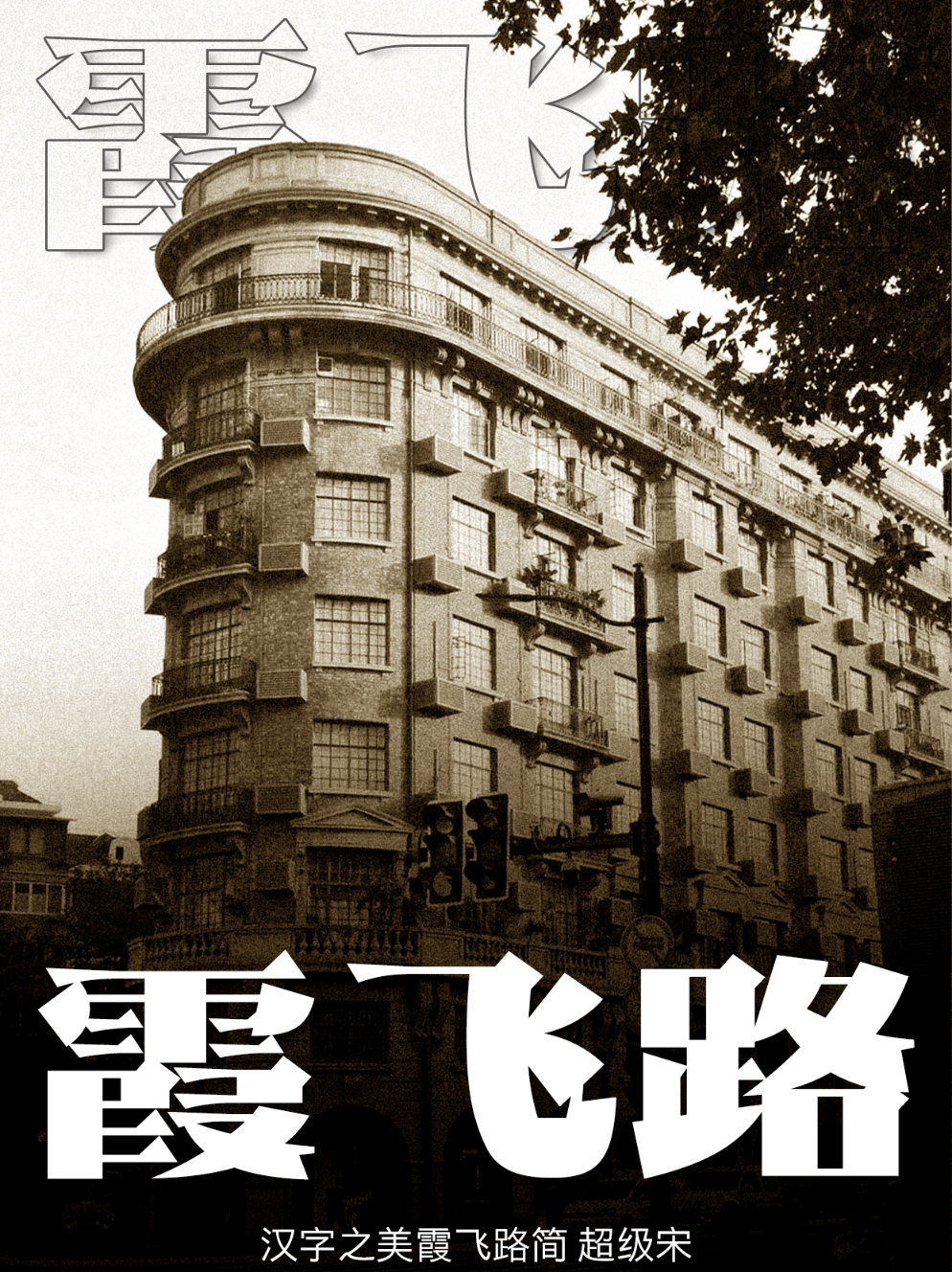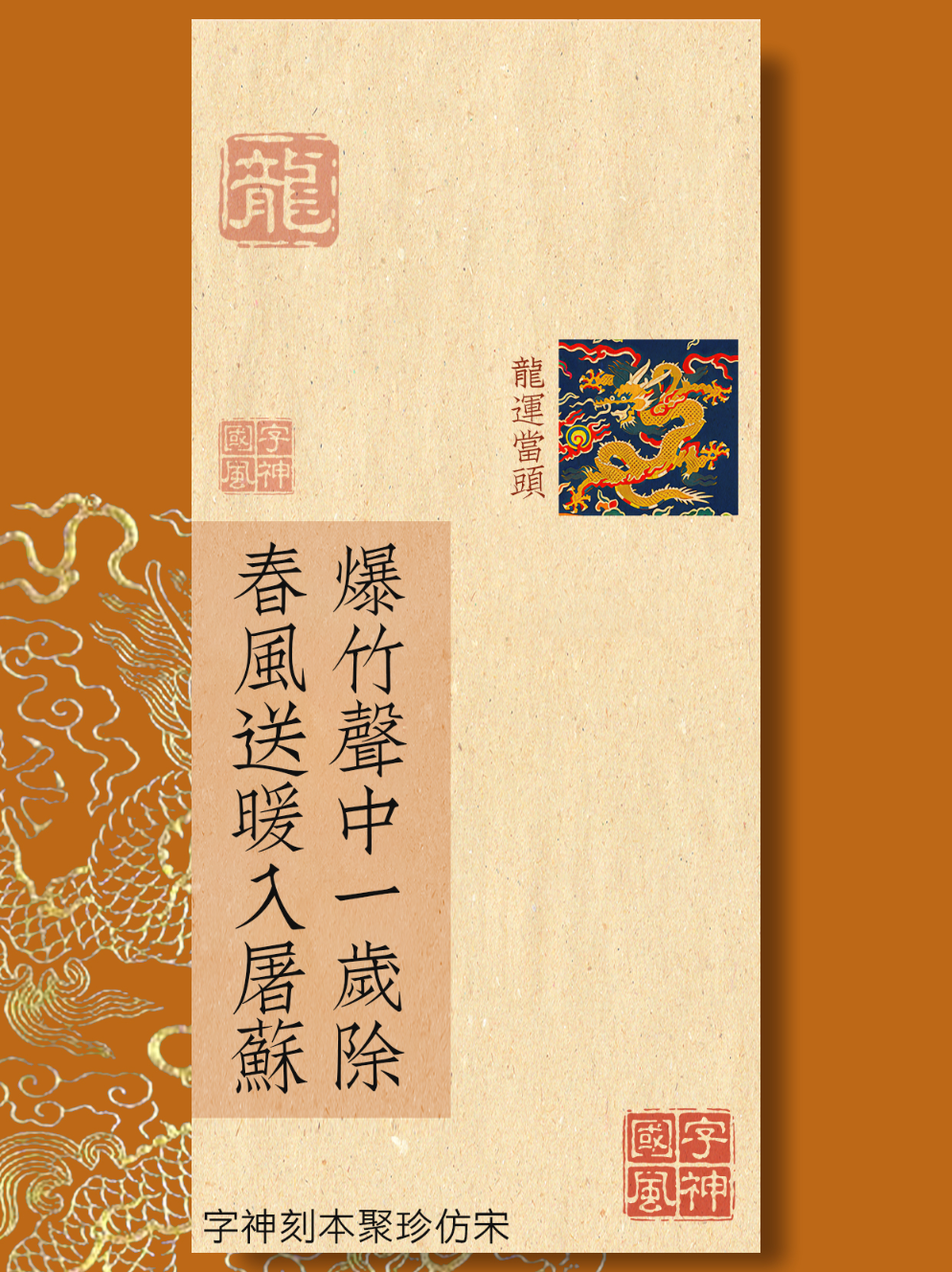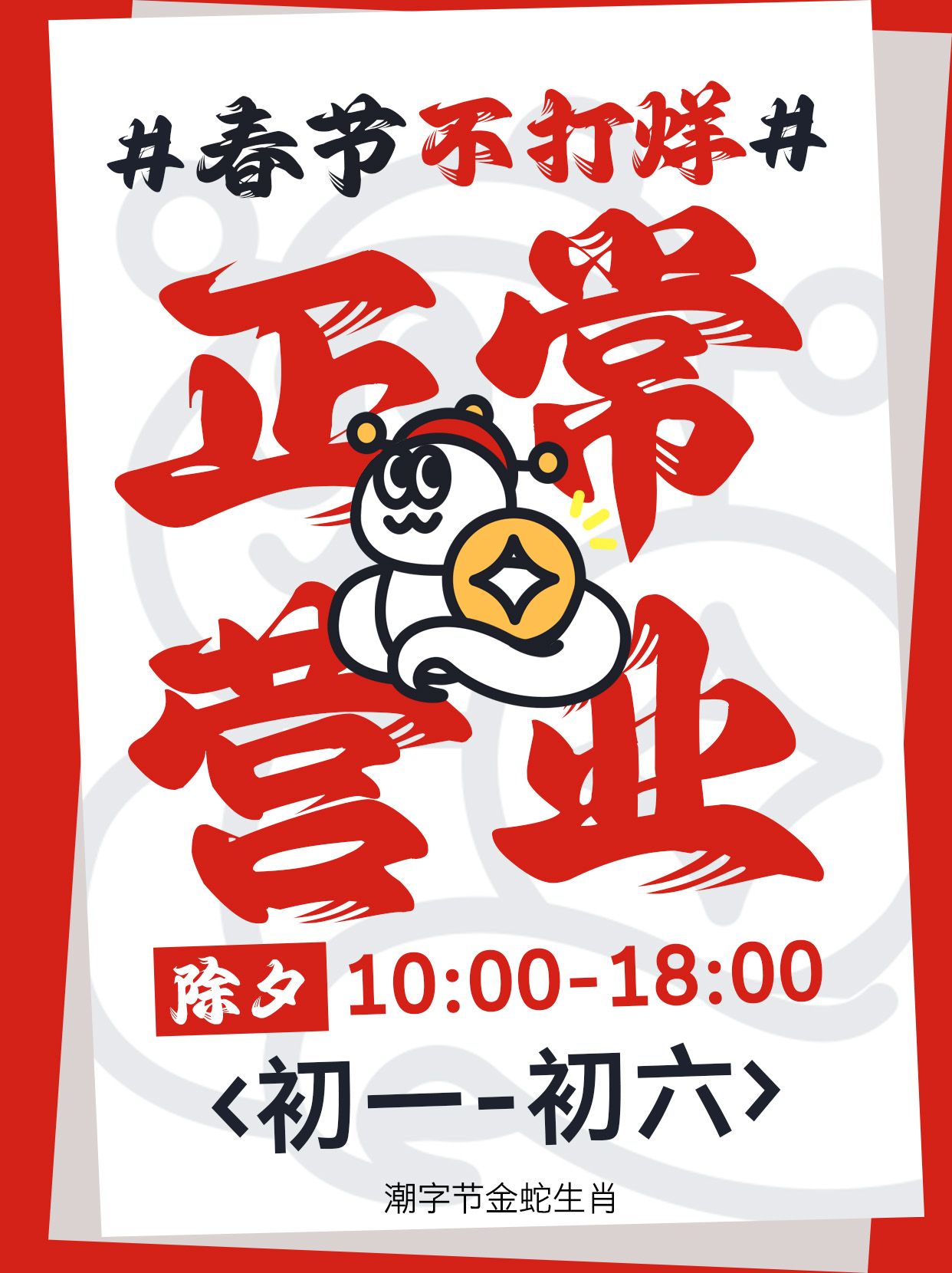
1️⃣ 汉字之美霞飞路简 —— 复古韵味,尽显雅致
这款字体简直就是为复古风礼盒量身定制的!霞飞路简以其独特的笔画设计和优雅的排版,让人一眼就爱上。它的线条流畅而不失力度,每一个字都仿佛在诉说着岁月的故事。用在女神节的包装上,绝对能让礼物散发出一种低调而奢华的气息。👑复古控们,赶紧把它加入购物车吧!
2️⃣ 字神刻本聚珍仿宋 —— 经典再现,雅致不凡
仿宋字体一直以其端庄、秀丽的特点受到大家的喜爱。而字神刻本聚珍仿宋更是将这一特点发挥到了极致。它的笔画清晰有力,结构严谨而不失灵动,用在女神节的包装上,既能彰显出礼物的品质感,又能让女神们感受到你的用心与品味。💖想要打造一份独一无二的女神节礼物?选它就对了!
3️⃣ 潮字节金蛇生肖 —— 创意无限,个性十足
如果你想要给女神们一个惊喜,那么潮字节金蛇生肖字体绝对是你的不二之选!这款字体将传统的生肖元素与现代设计巧妙结合,既保留了传统文化的韵味,又充满了时尚感和创意。用在女神节的包装上,不仅能让礼物瞬间脱颖而出,还能让女神们感受到你的独特品味和满满的心意。🎉快来用它为你的女神节礼物增添一份别样的风采吧!